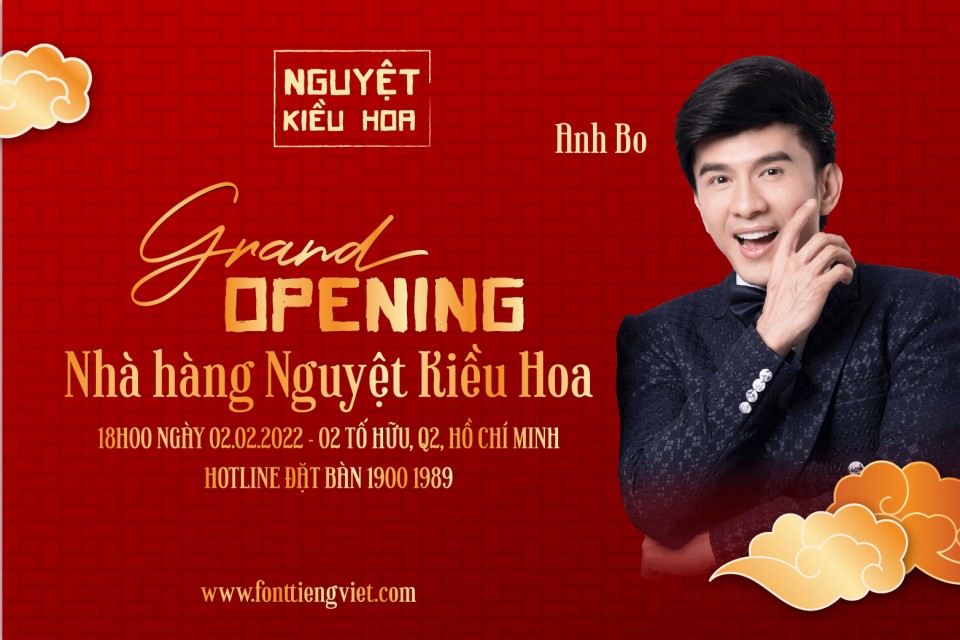
Combo font thiết kế khai trương 3 + Kèm file thiết kế Ai chủ đề nhà hàng
Chào mừng các bạn đến với kho lưu trữ tài nguyên đồ họa chuyên nghiệp dành cho ngành dịch vụ ăn uống. Trong bài viết hôm nay, chúng tôi xin giới thiệu bộ Combo font thiết kế khai trương 3 + Kèm file thiết kế Ai chủ đề nhà hàng, một giải pháp hoàn thiện giúp các bạn học sinh, sinh viên và những người mới bắt đầu làm quen với lĩnh vực thiết kế có thêm tư liệu chất lượng. Việc lựa chọn Font Miễn Phí phù hợp không chỉ giúp bản thiết kế trở nên bắt mắt mà còn truyền tải đúng tinh thần sang trọng hoặc ấm cúng của một không gian ẩm thực trong ngày đầu ra mắt khách hàng.
Tầm quan trọng của Combo font thiết kế khai trương 3 + Kèm file thiết kế Ai chủ đề nhà hàng
Khi thực hiện các dự án thiết kế cho sự kiện khai trương nhà hàng, việc kết hợp giữa font chữ và hình ảnh minh họa đóng vai trò then chốt. Combo font thiết kế khai trương 3 + Kèm file thiết kế Ai chủ đề nhà hàng được tuyển chọn kỹ lưỡng để đảm bảo tính thẩm mỹ cao và sự đồng nhất trong nhận diện thương hiệu. Các mẫu thiết kế kèm theo định dạng Adobe Illustrator (Ai) cho phép người dùng tùy chỉnh linh hoạt từ màu sắc đến bố cục mà không lo vỡ nét.
Ưu điểm khi sử dụng file thiết kế Ai chuyên nghiệp
File Ai đi kèm trong bộ combo này bao gồm các mẫu menu, băng rôn và thiệp mời đã được dàn trang sẵn. Người dùng chỉ cần thay đổi nội dung chữ dựa trên danh sách font có sẵn để tạo ra sản phẩm hoàn chỉnh. Điều này giúp tiết kiệm tối đa thời gian cho các bạn học tập tại trường lớp khi thực hành thiết kế quảng cáo thực tế. Các lớp layer được sắp xếp khoa học giúp việc thao tác trở nên dễ dàng và hiệu quả hơn rất nhiều.
Chi tiết các loại font trong bộ Combo font thiết kế khai trương 3
Bộ sưu tập này tập trung vào hai dòng phong cách chính: hiện đại và cổ điển. Đối với các nhà hàng Á Đông, bộ combo cung cấp những font chữ có nét bút lông mạnh mẽ, tạo cảm giác truyền thống. Ngược lại, với các nhà hàng Âu Mỹ, các font chữ không chân (sans-serif) thanh mảnh sẽ mang lại cảm giác tinh tế và thời thượng cho các ấn phẩm khai trương.
Font chữ việt hóa giúp tối ưu nội dung tiếng Việt
Điểm đặc biệt của Combo font thiết kế khai trương 3 + Kèm file thiết kế Ai chủ đề nhà hàng chính là toàn bộ các font chữ đều đã được việt hóa hoàn chỉnh. Bạn sẽ không gặp phải các lỗi hiển thị dấu tiếng Việt như “ô”, “ơ” hay “ư” bị lỗi font. Đây là yếu tố cực kỳ quan trọng giúp bản thiết kế chuyên nghiệp hơn trong mắt khách hàng và thầy cô khi chấm bài tập thiết kế đồ họa.
Kết luận về bộ tài nguyên thiết kế nhà hàng